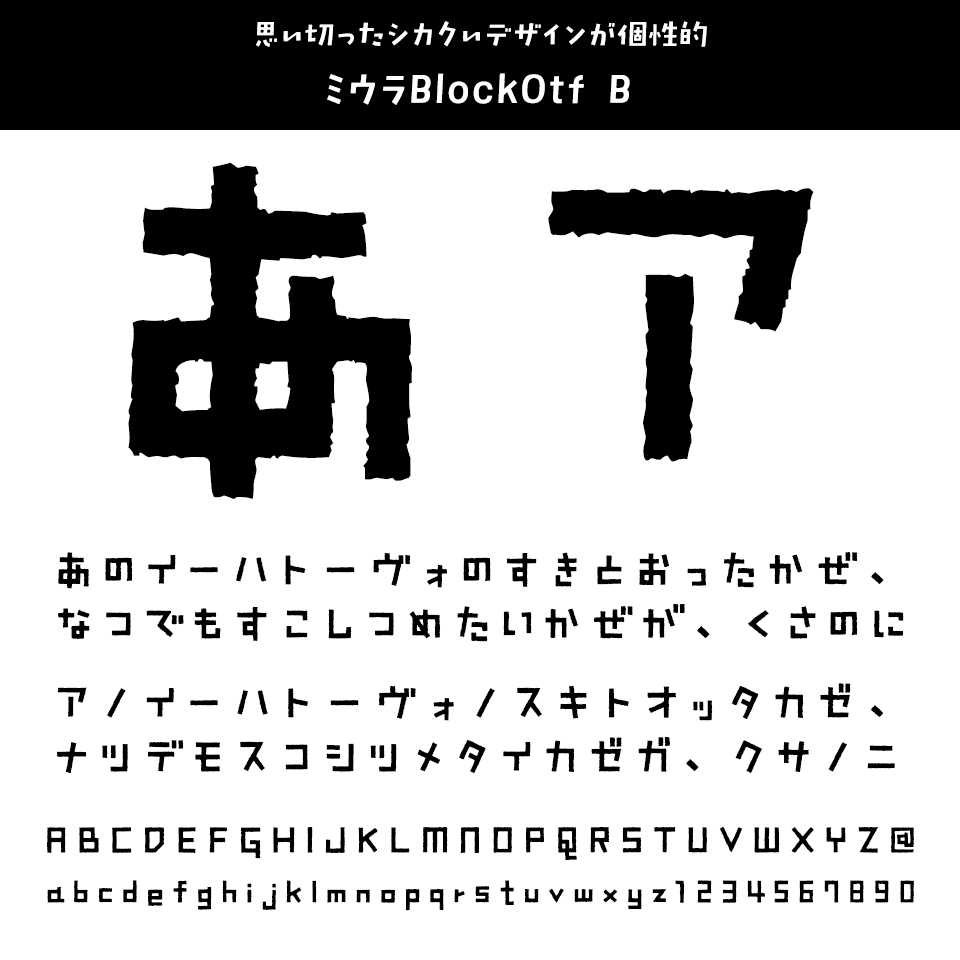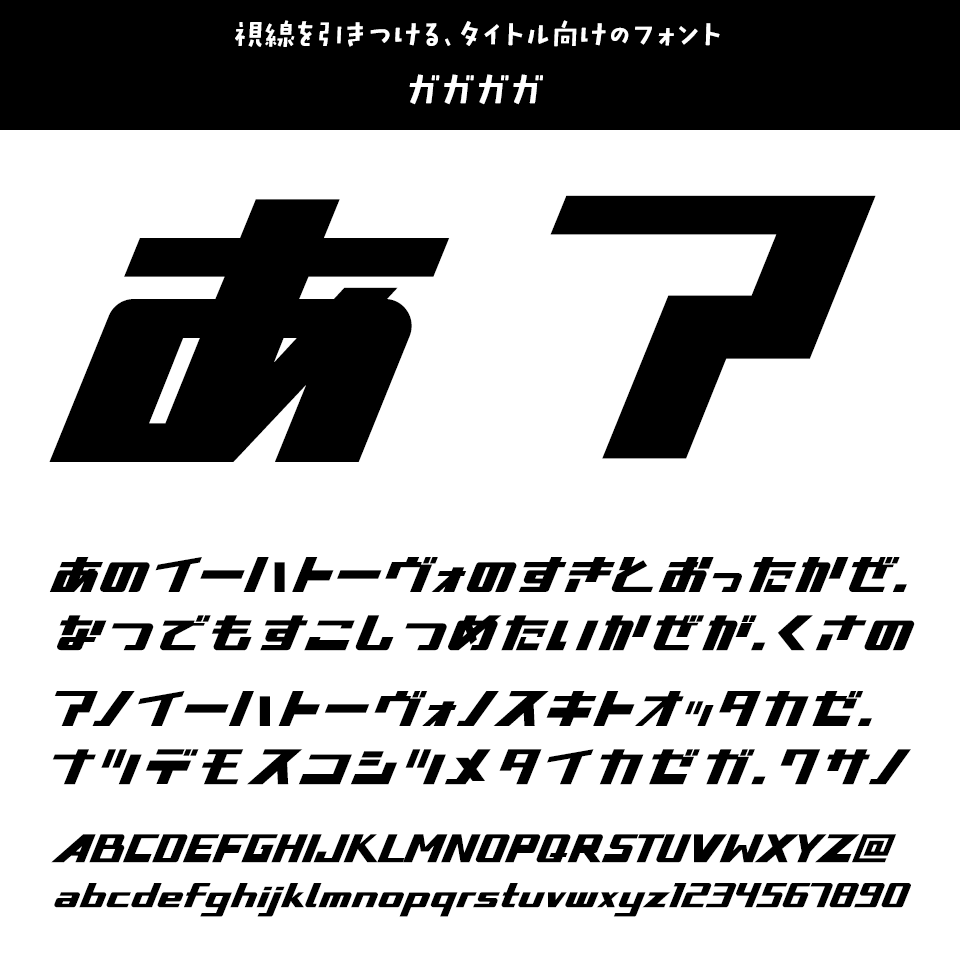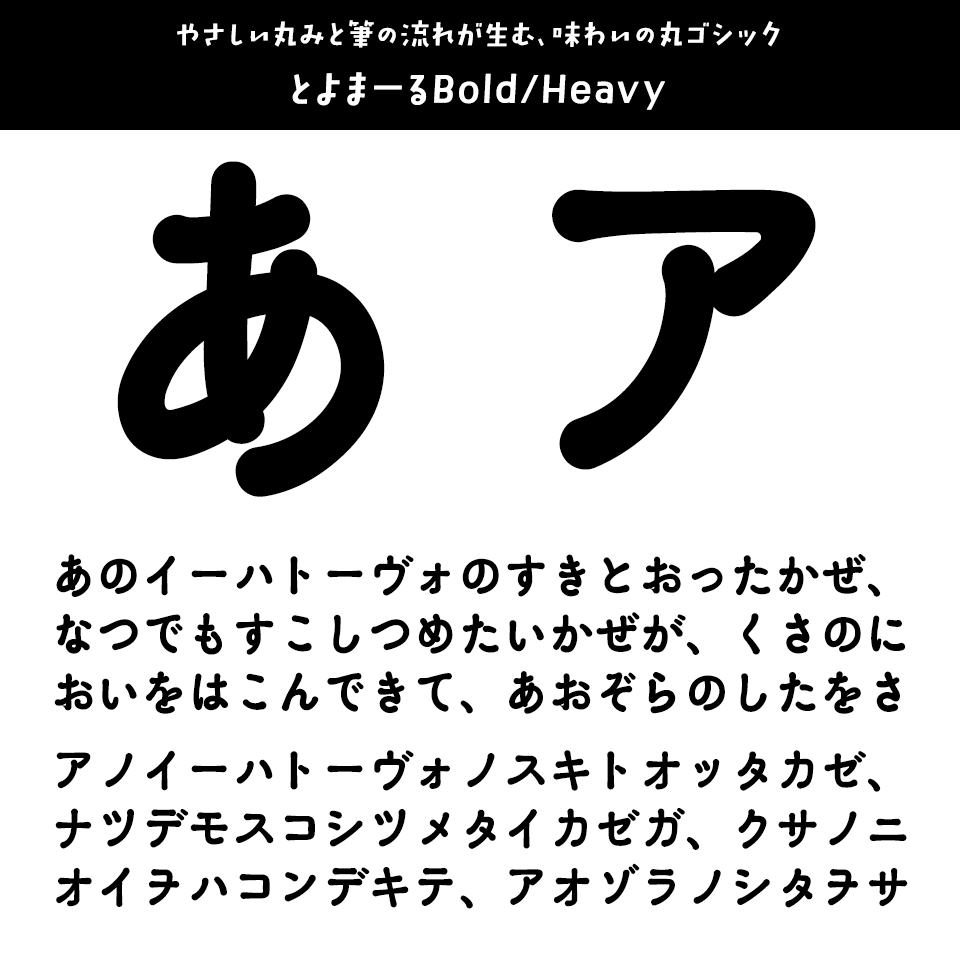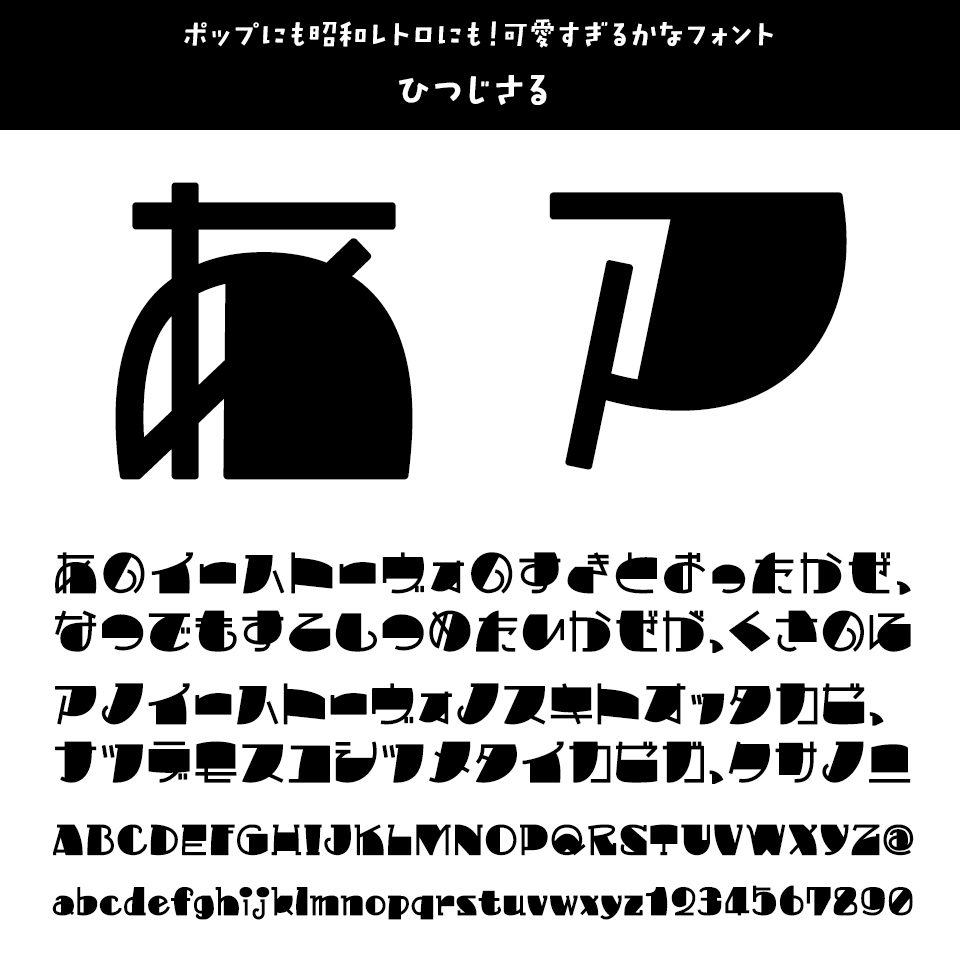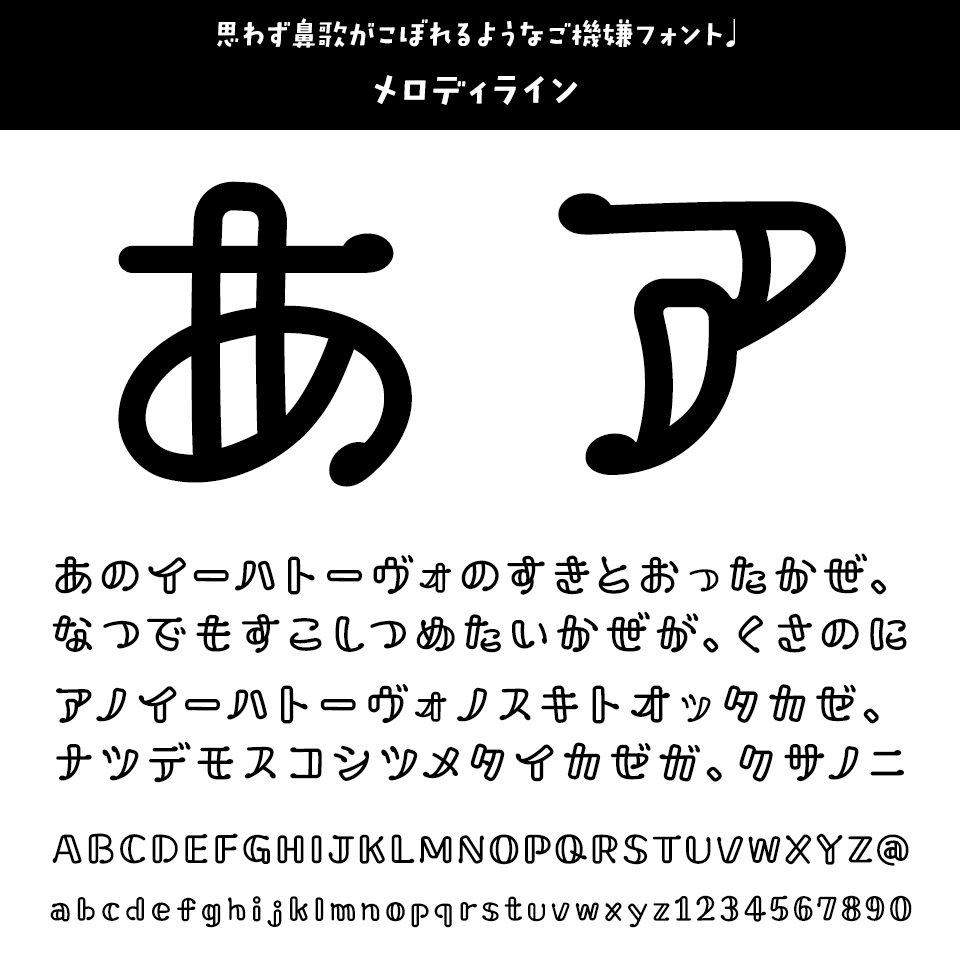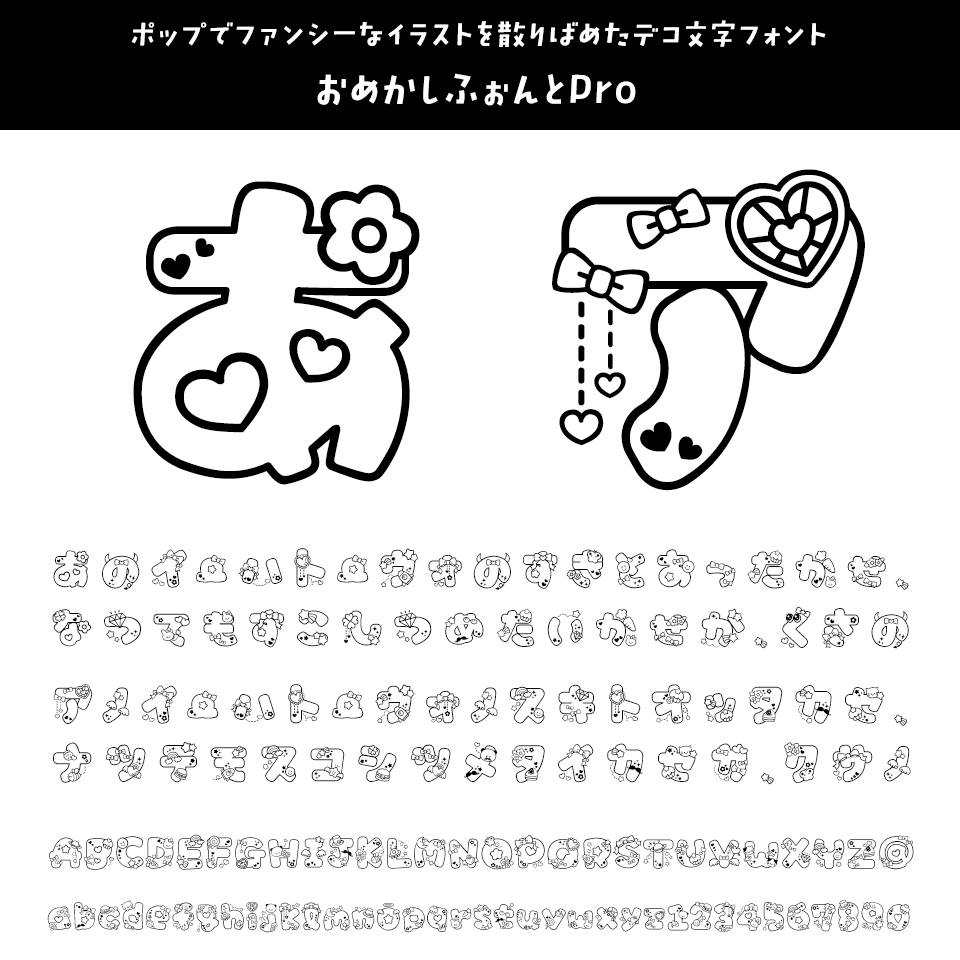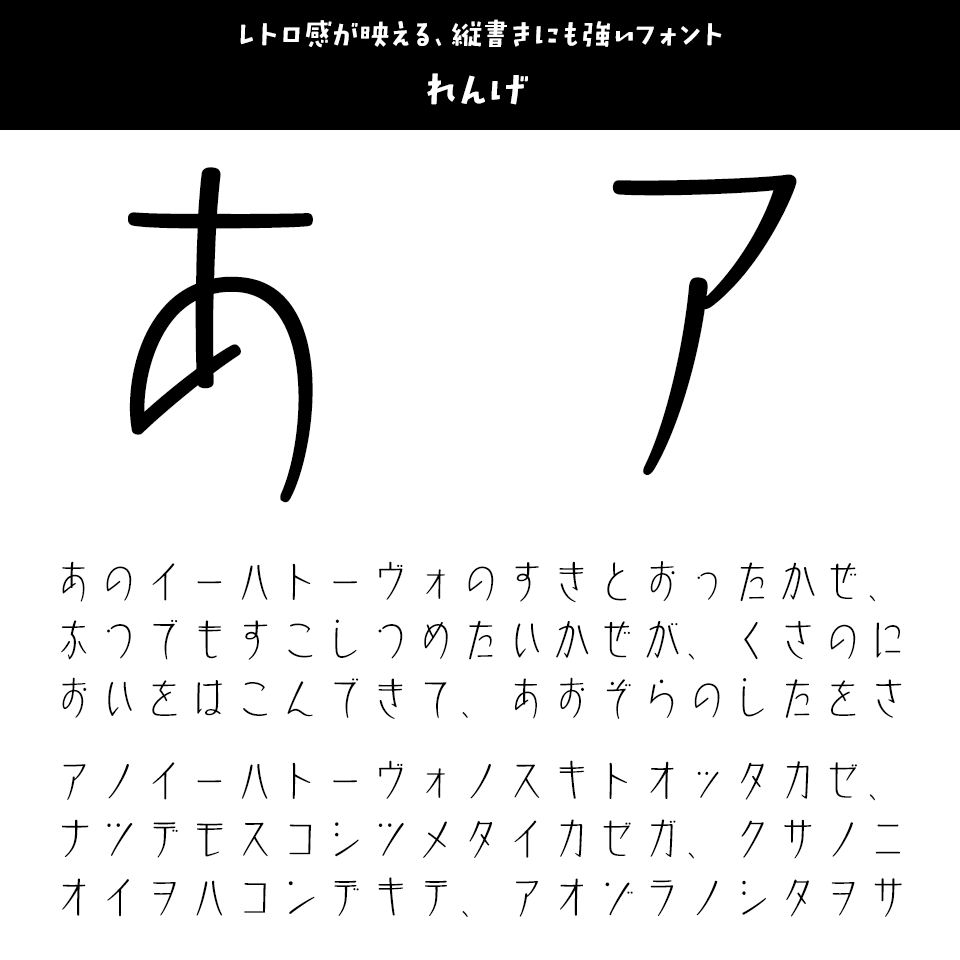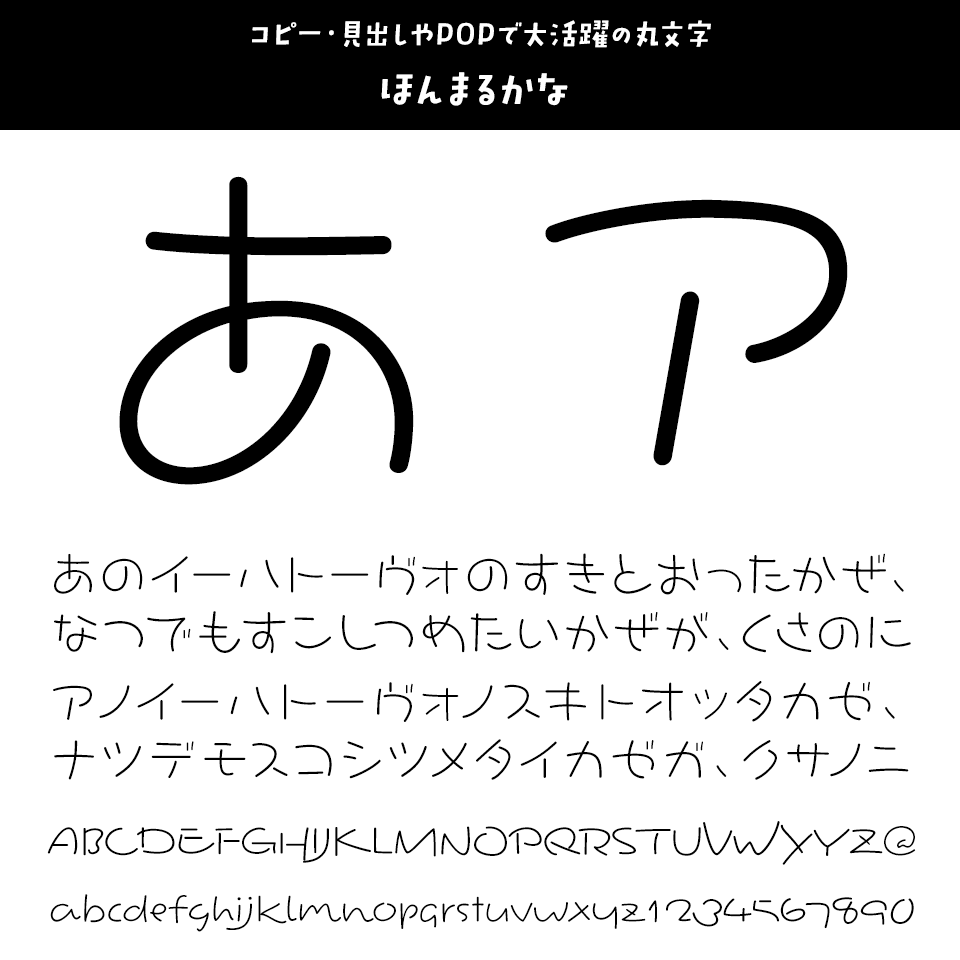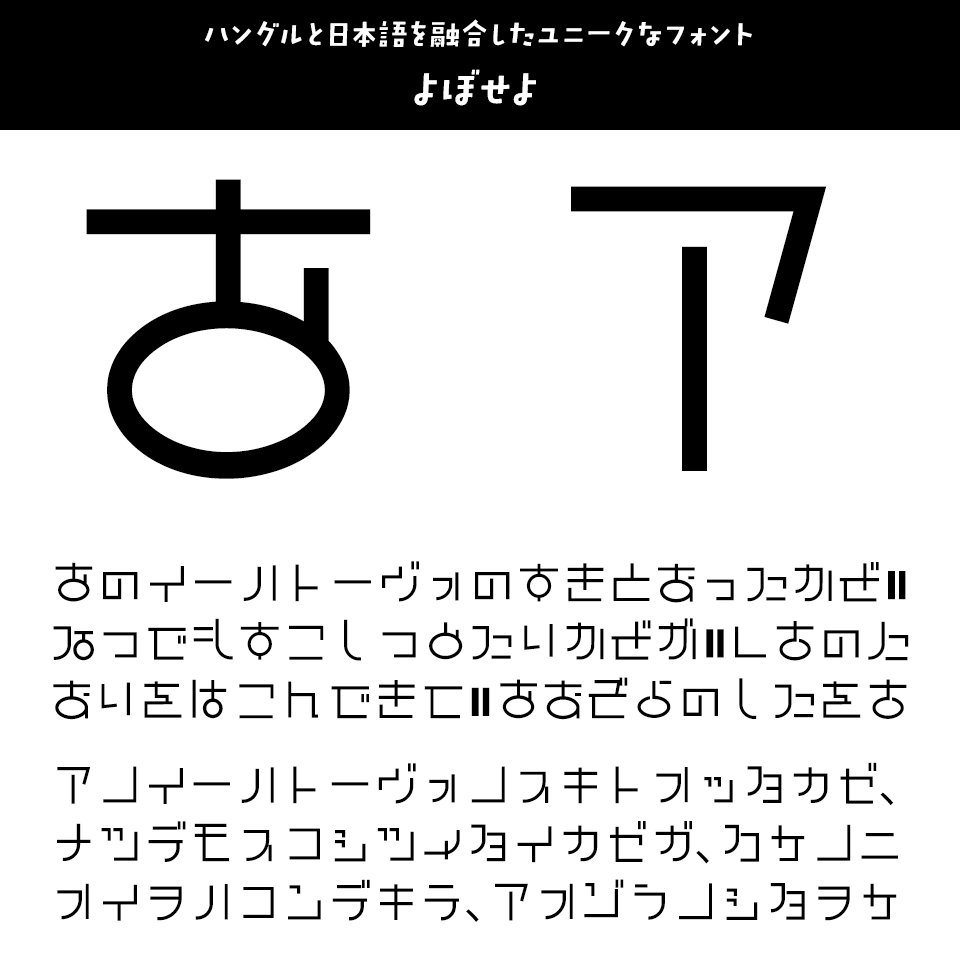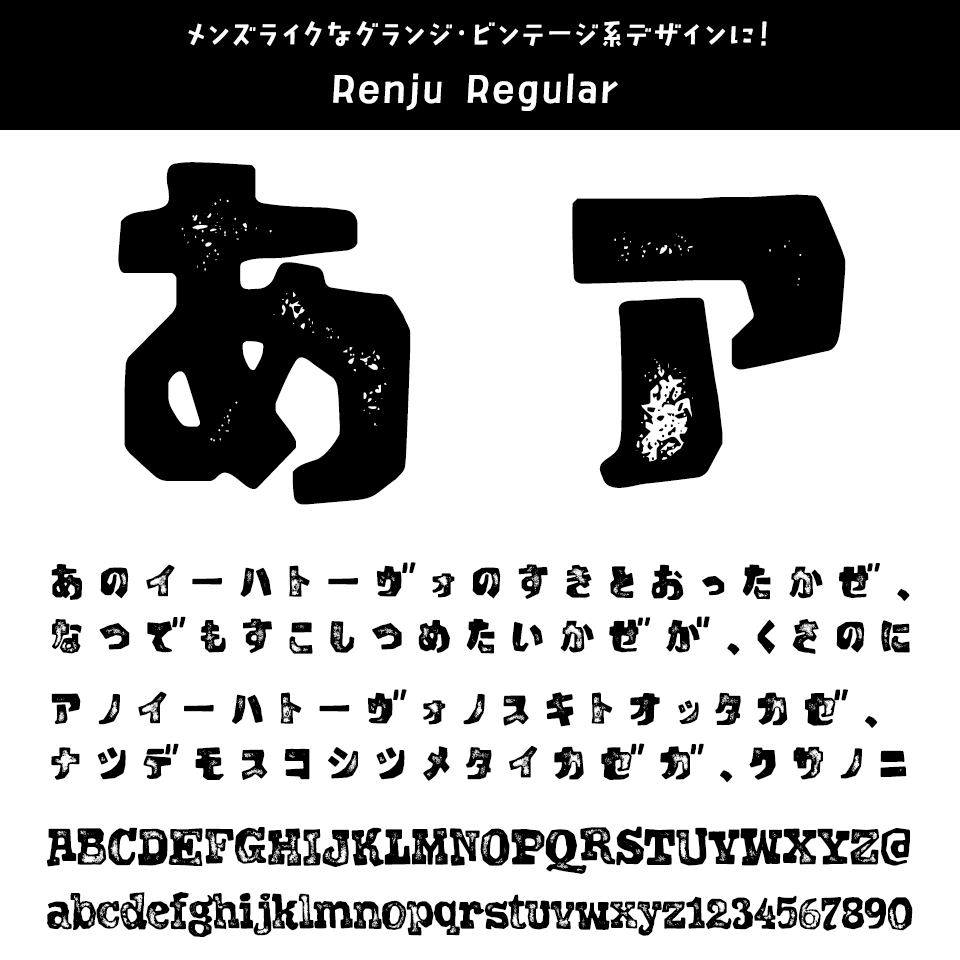
ひらがな・カタカナのフォント アングル
サイズ感調整が自在のオシャレな手書き風バリアブルフォント
ひらがな・カタカナのフォント アングル
やや右肩上がりの手書き文字のような大小のリズムある文字を作れる、バリアブル (可変) フォントです。
ひらがな・カタカナのフォント きしめんゴシック
きしめんのように平たく、伸びやかな画線が特色
ひらがな・カタカナのフォント きしめんゴシック
明治の最初期の築地体ゴシック体活字に見られる毛筆的な書風と造形を独自に読み解き、築地体明朝の骨格を参照しながらゴシック体へ再構成したかな書体です。制作にあたっては「守破離」を指針とし、既存の型を踏まえつつ独自性を鍛える「破」の段階に位置づけています。墨だまりのある「B1」版や、TTF版も同梱。
ひらがな・カタカナのフォント ミウラBlockOtf B
思い切ったシカクいデザインが個性的
ひらがな・カタカナのフォント ミウラBlockOtf B
ミウラLinerやミウラ見出しLinerとも相性のよい、可愛らしさ満点の仮名文字フォント。
ひらがな・カタカナのフォント ガガガガ
視線を引きつける、タイトル向けのフォント
ひらがな・カタカナのフォント ガガガガ
個性的な造形のひらがな・カタカナが、タイトルや見出しで強い存在感を発揮。短い言葉でも視線を集め、ポスターやバナー、動画タイトルなど注目させたいデザインに最適です。
ひらがな・カタカナのフォント とよまーるBold/Heavy
やさしい丸みと筆の流れが生む、味わいの丸ゴシック
ひらがな・カタカナのフォント とよまーるBold/Heavy
丸ゴシックの柔らかさに、筆の流れやストロークの強弱を加えた表情豊かな書体。ひらがな・カタカナのやさしい雰囲気が際立ち、親しみやすく温かみのあるデザインを演出できます。
ひらがな・カタカナのフォント ひつじさる
ポップにも昭和レトロにも!可愛すぎるかなフォント
ひらがな・カタカナのフォント ひつじさる
文字の一部が極太になっている、インパクトのあるフォントです。ひらがなとカタカナは、一つの文字に対して2種類の字形 ( 01Default / 02Alt ) を用意しました。
ひらがな・カタカナのフォント メロディライン
思わず鼻歌がこぼれるようなご機嫌フォント♩
ひらがな・カタカナのフォント メロディライン
「メロディライン」は音符をモチーフにしたインラインフォントです。記号を入力して、音符に変換することができます。
ひらがな・カタカナのフォント おめかしふぉんとPro
ポップでファンシーなイラストを散りばめたデコ文字フォント
ひらがな・カタカナのフォント おめかしふぉんとPro
ひらがな・カタカナのフォント れんげ
レトロ感が映える、縦書きにも強いフォント
ひらがな・カタカナのフォント れんげ
レトロな雰囲気をまとったひらがな・カタカナが魅力の書体。字幕や見出しなど短い言葉でも存在感があり、縦書きでもバランスよく美しく整います。映像字幕やレトロデザインにぴったりです。
ひらがな・カタカナのフォント ほんまるかな
コピー・見出しやPOPで大活躍の丸文字
ひらがな・カタカナのフォント <strong>ほんまるかな</strong>
かすかに筆文字の名残り、味わいのある丸もじ。やや左上に重心がある独特のフォルム。
ひらがな・カタカナのフォント よぼせよ
ハングルと日本語を融合したユニークなフォント
ひらがな・カタカナのフォント <strong>よぼせよ</strong>
ハングルっぽいカナフォント。韓国語で電話をかける時・受ける時の定型句「ヨボセヨ」をイメージしました。
ひらがな・カタカナのフォント Renju Regular
メンズライクなグランジ・ビンテージ系デザインに!
ひらがな・カタカナのフォント <strong>Renju Regular</strong>
デザインコンシャスな欧文フォント。英語の他、ドイツ語・フランス語・スペイン語など20以上の言語を表現可能。